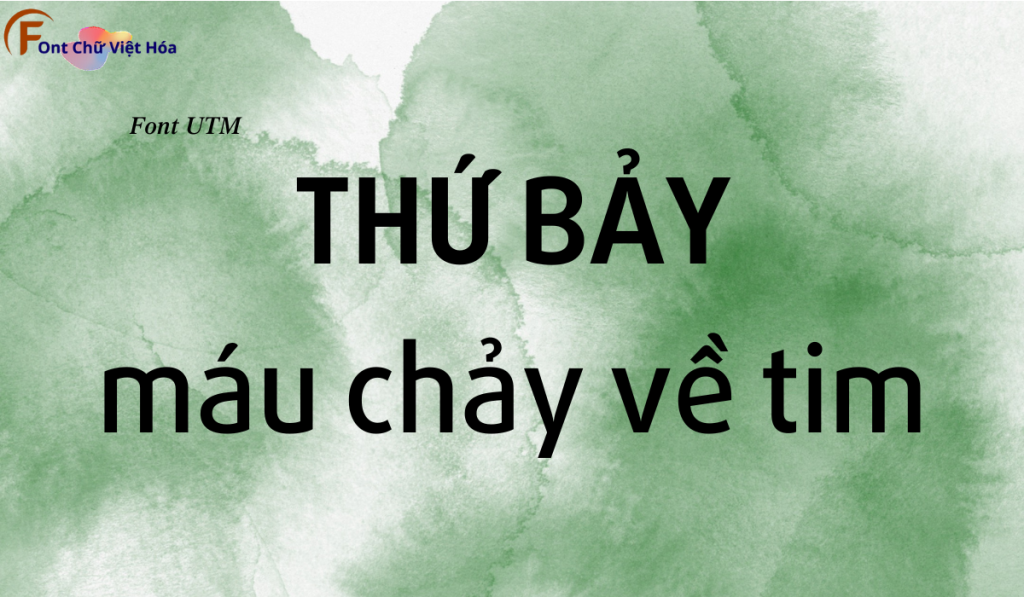
Font UTM Daxline Việt Hóa
Kiểu chữ: Sans-serif
Font UTM Daxline Việt Hóa là một font chữ không chân cá tính, thuộc bộ font UTM. Được thiết kế với mục tiêu mang lại sự độc đáo và sáng tạo, font này lý tưởng cho các dự án thiết kế như logo, poster, và bao bì sản phẩm. Với các nét chữ sắc nét và độ dày đều đặn, Font UTM Daxline Việt Hóa không chỉ dễ đọc mà còn tạo cảm giác hiện đại và phá cách. Việc Việt hóa font giúp người dùng dễ dàng tích hợp vào các thiết kế tiếng Việt, mang lại sự tiện lợi và nâng cao tính thẩm mỹ.